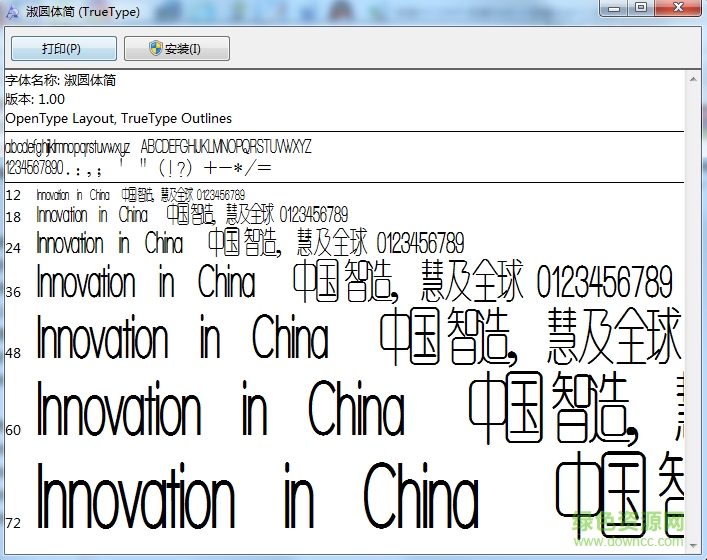
淑圓體是一款簡(jiǎn)瘦細(xì)長(zhǎng)的中文簡(jiǎn)體,字跡精簡(jiǎn)大方,適用于文章排版、海報(bào)設(shè)計(jì)、平面印刷等多種行業(yè),歡迎大家在綠色資源網(wǎng)免費(fèi)下載使用!
淑圓體是一款風(fēng)格獨(dú)特的中文簡(jiǎn)體,簡(jiǎn)單秀麗的造型給人獨(dú)特的好感,企鵝本字體完整不缺字,喜歡的朋友快來體驗(yàn)吧!